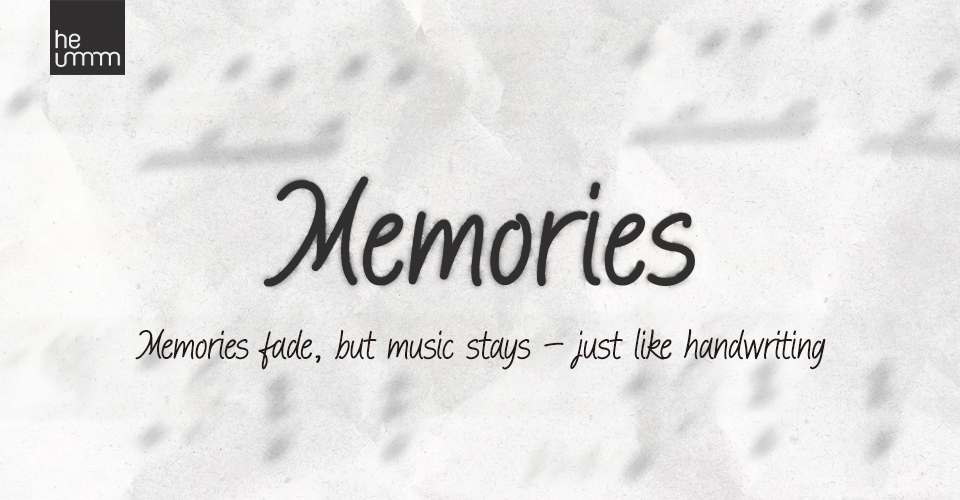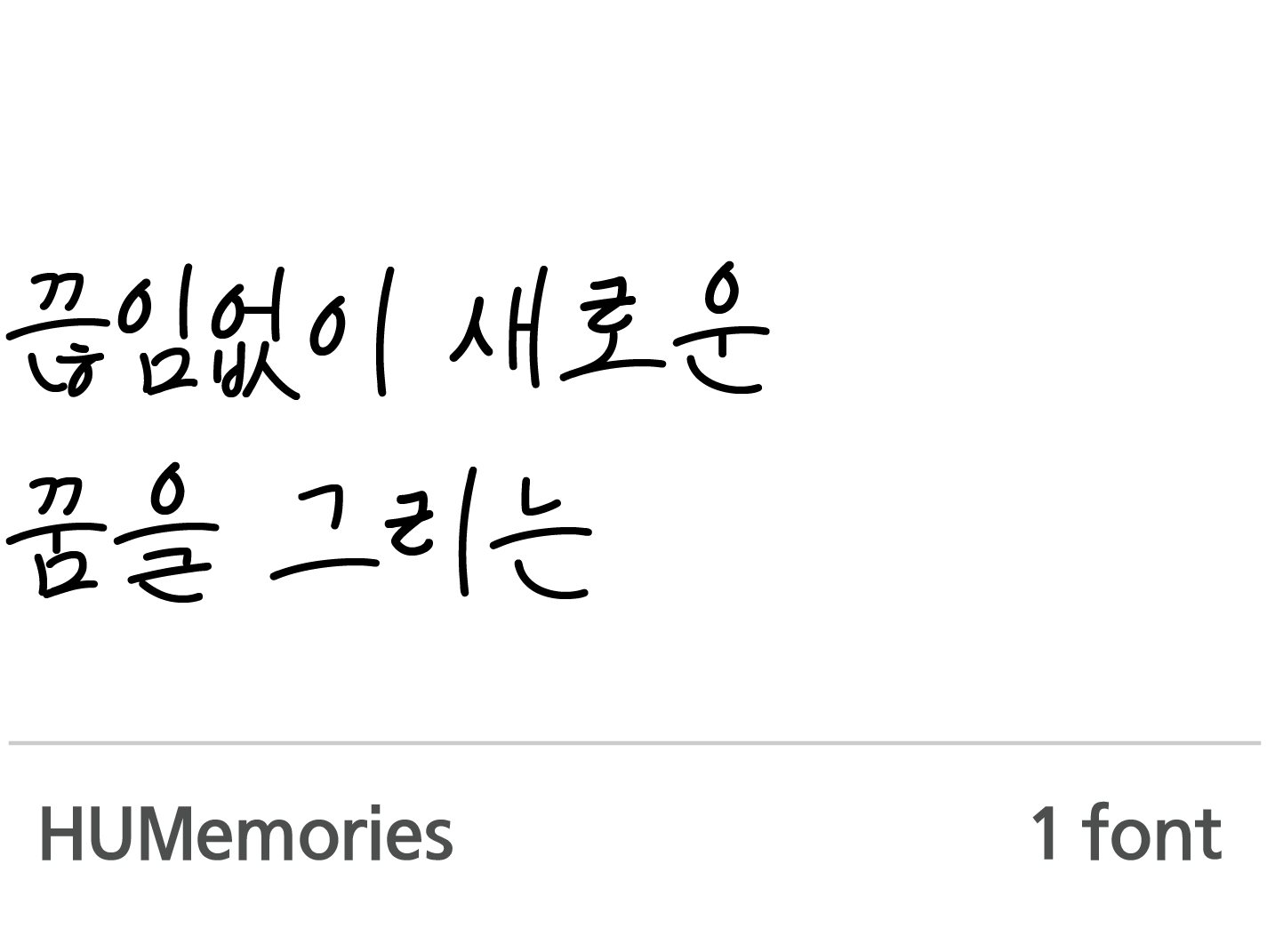
폰트      HUMemories
굵기      1종
기간      2025
구성      KS한글 11,172자
최대한 예쁘게 보이고 싶어 또박또박 쓰고, 멋드러지게 쓰고 싶으나 휘날려 쓰게 되던 손글씨의 느낌을 담은 손글씨 서체입니다.
HUMemories Regular